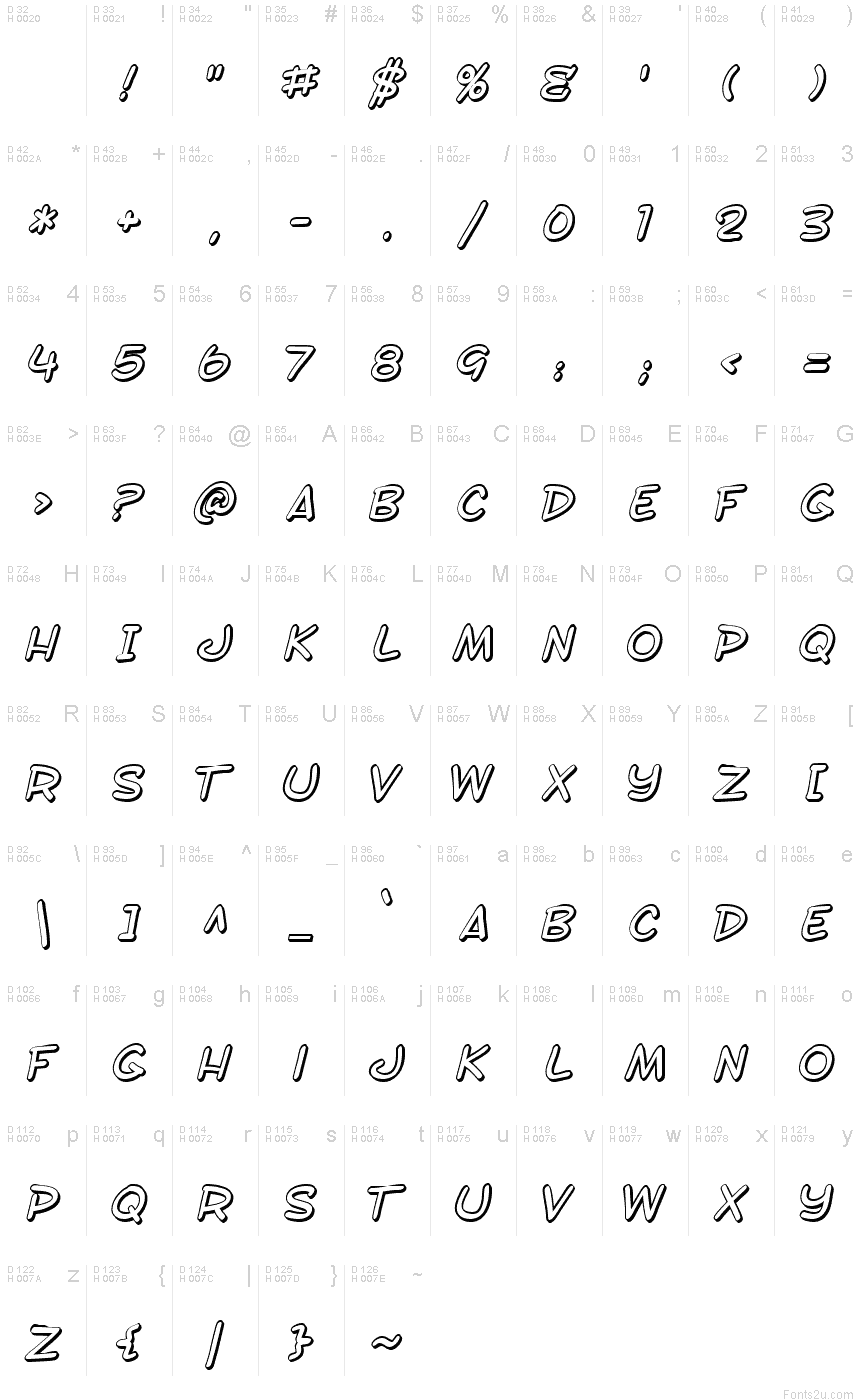
SF Toontime Shaded Italic
SF Toontime Shaded Italic od ShyFoundry to darmowy, trójwymiarowy font typu display w stylu kreskówkowym. Charakteryzuje się dużymi, zaokrąglonymi wielkimi literami, które są pochylone do przodu, przywodząc na myśl napisy z komiksowych tytułów. Litery są miękkie i wypukłe, z wyraźnym obrysem oraz delikatnie przesuniętym cieniem, co nadaje krojowi sprężystego, gumowego charakteru.
Świetnie sprawdzi się na plakatach, zaproszeniach na przyjęcia dla dzieci, okładkach komiksów, w tytułach gier, na opakowaniach przekąsek oraz w krótkich logotypach, gdzie darmowy font ma natychmiastowo wprowadzić zabawny klimat bez zbędnego zadęcia. Dzięki szerokim, przyjaznym i lekko pochylonym wielkim literom, sprawdzi się również w wyrazistych nagłówkach i krótkich monogramach, którym chcesz dodać nieco figlarnego charakteru.
ShyFoundry
Derek Vogelpohl